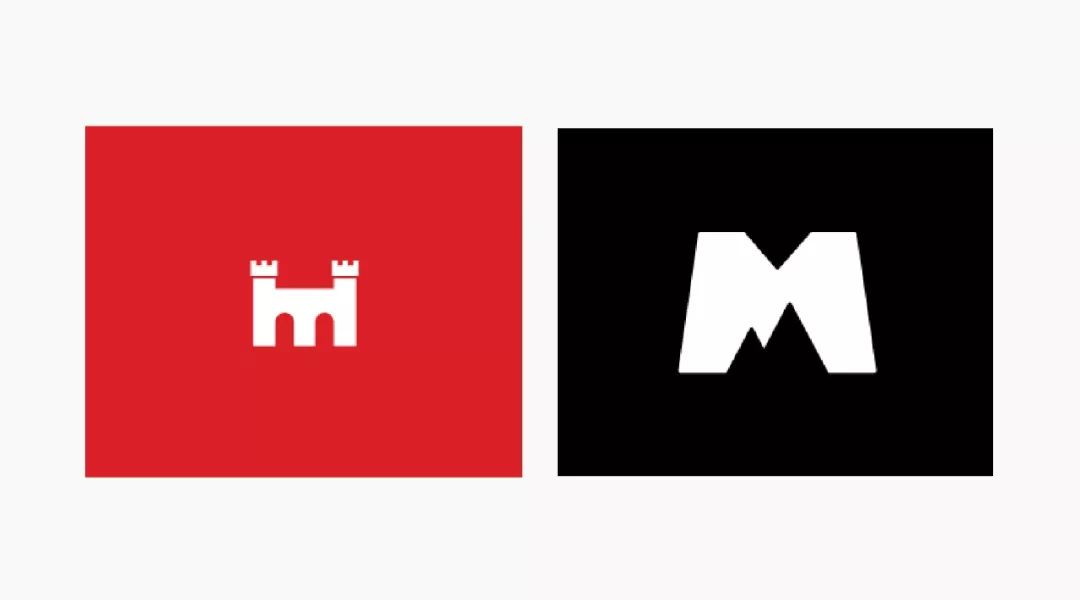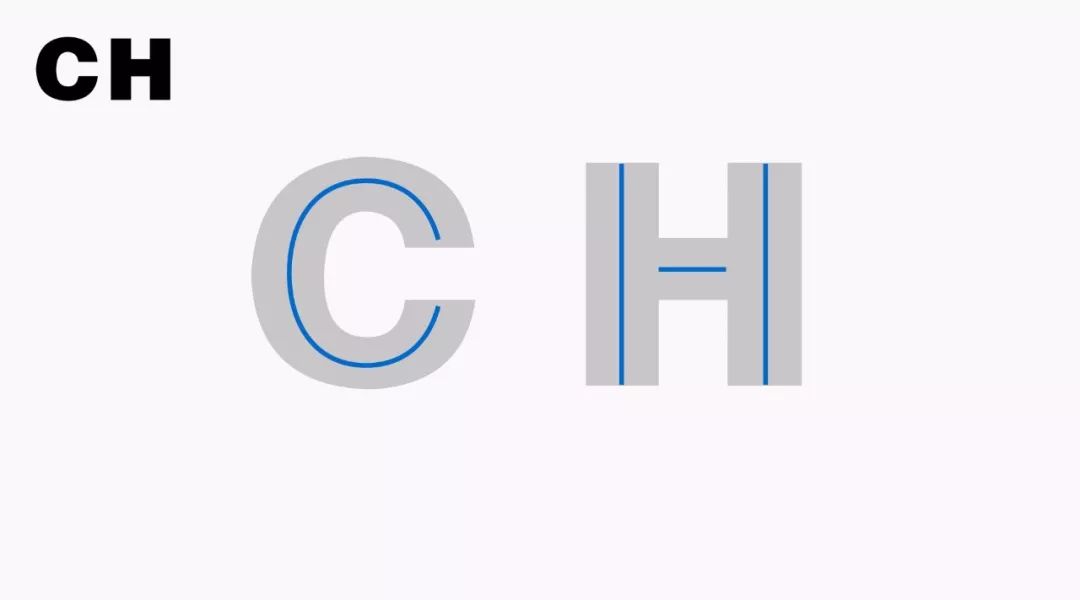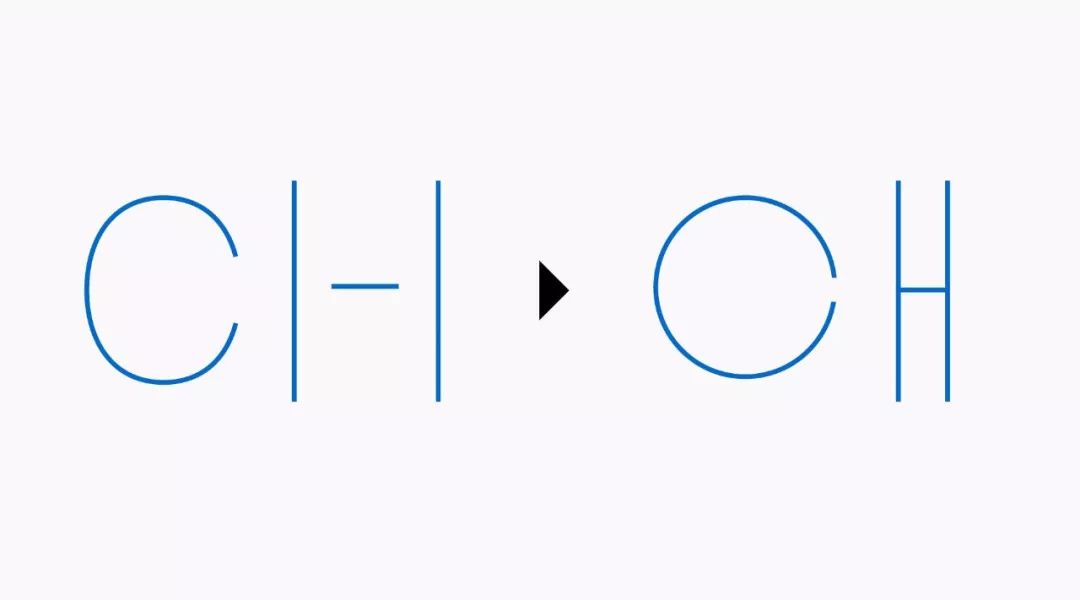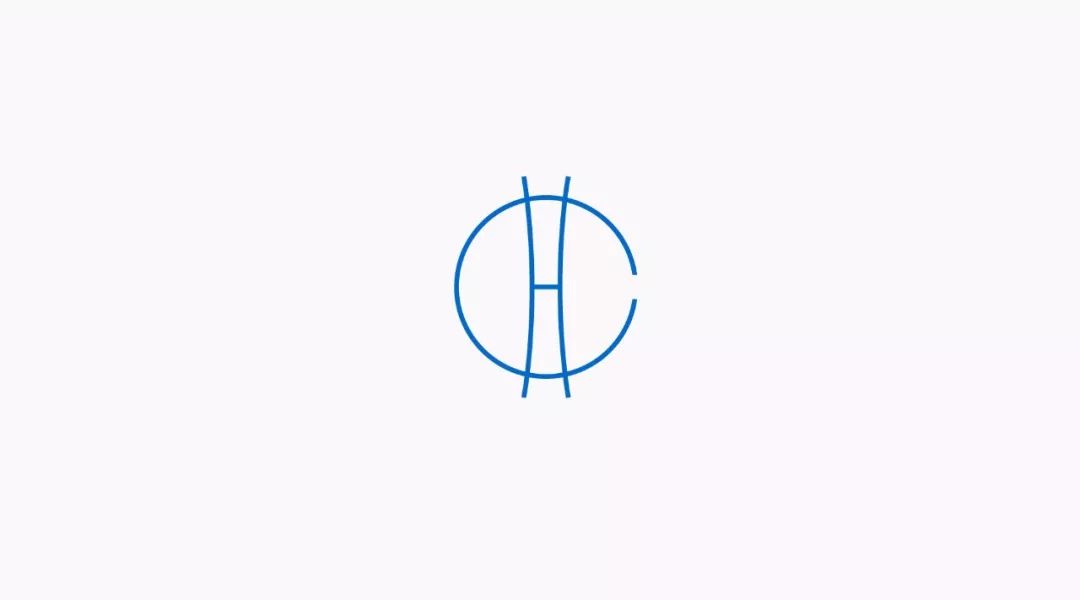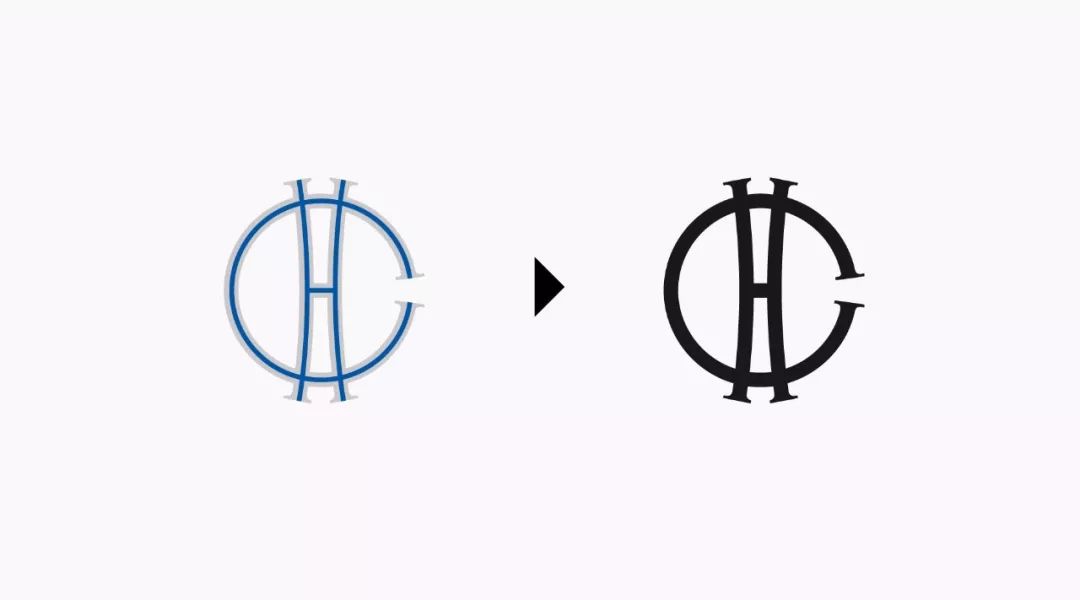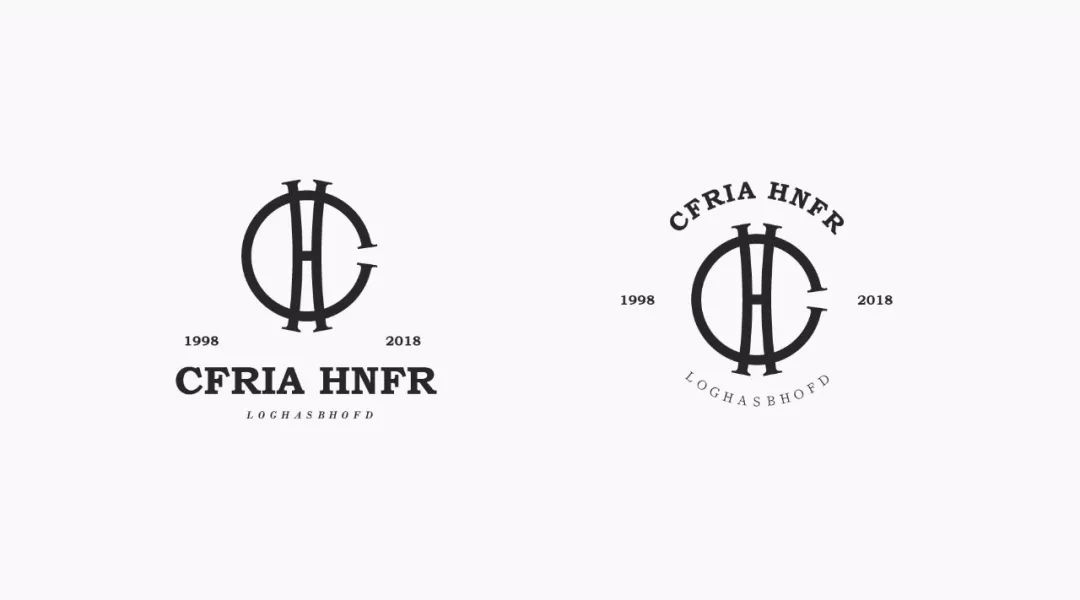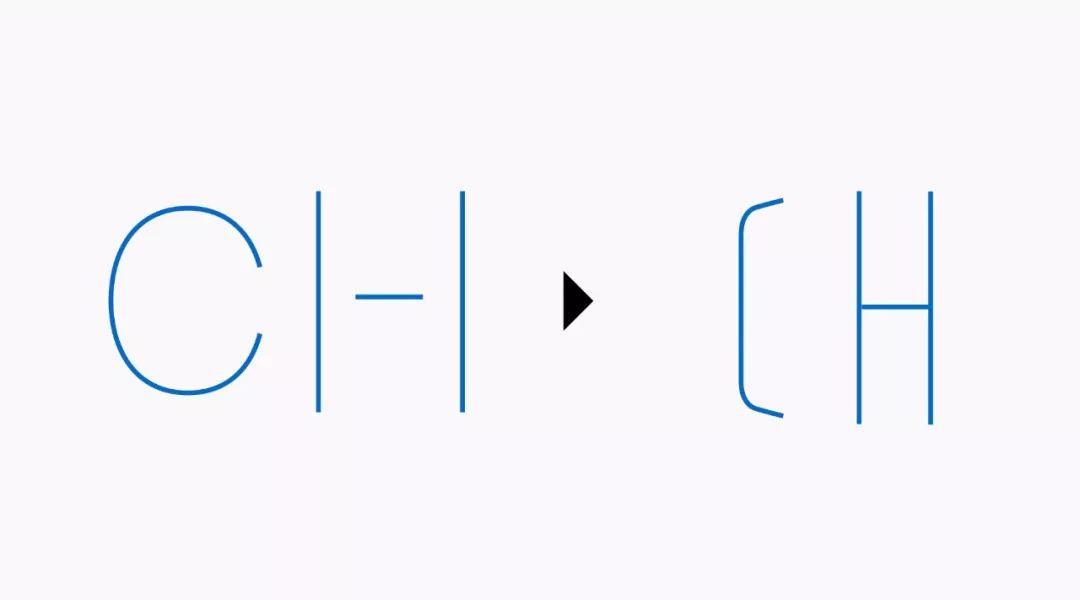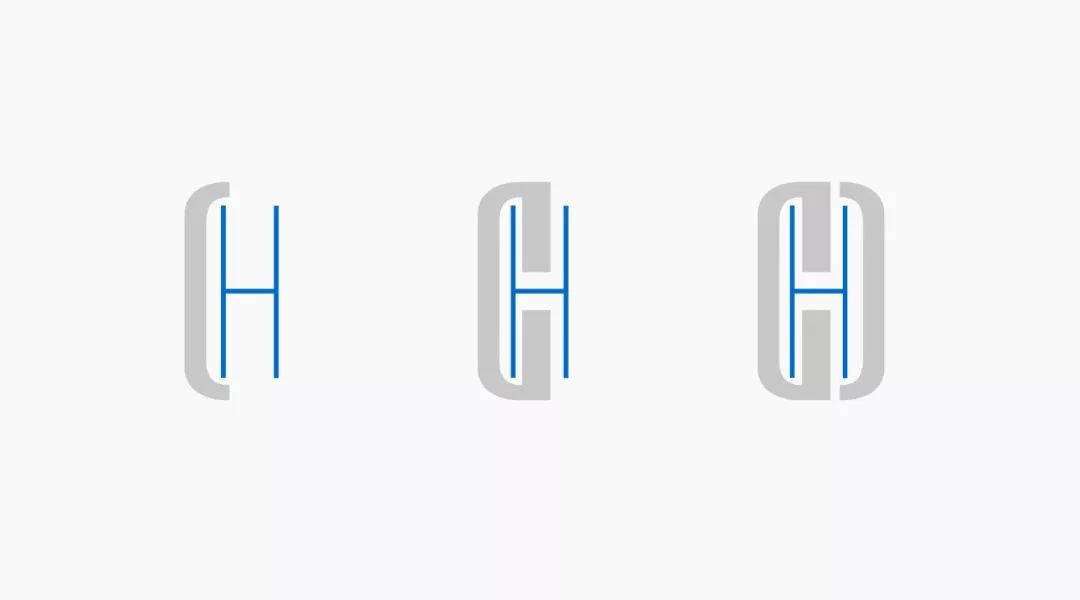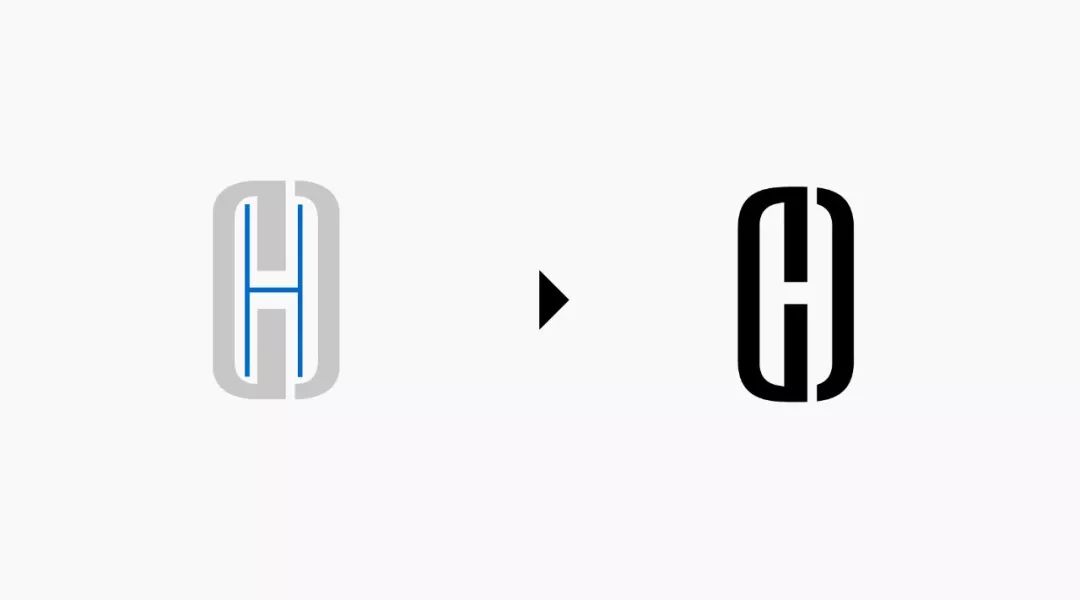
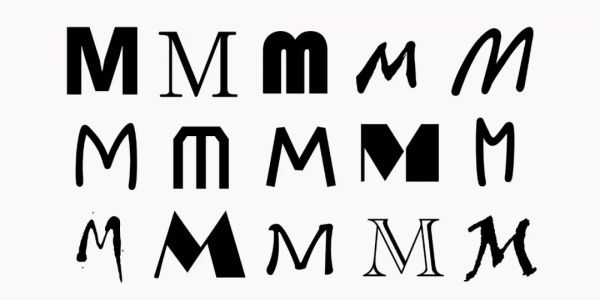
如何用首字母做一个漂亮的LOGO?
为什么很多公司用首字母做LOGO?
很多公司都用首字母或者首汉字做公司LOGO设计的元素,首字母的标志会把LOGO和品牌名称更紧密的联系起来了,减小了消费者看到LOGO后对其品牌的认知成本。
拿Mcdonald's和KFC为例子,如果你从未听说过这两个品牌LOGO,但是你得知一个品牌叫KFC,另一个是叫Mcdonald's,你会自然而然的把M的LOGO猜测成Mcdonald's,但KFC你就不能如此确定了。
所以首字母的LOGO更方便消费者最快速度建立标志和品牌之间的关系,达到认知和记忆效果。那我们如何去做一个优秀的首字母LOGO呢?
字母与具体元素结合
了解如何做一个首字母LOGO,就要先了解首字母LOGO有哪些种类,本文共提供3种首字母LOGO,其一是字母与具体元素结合,比如字母+动物,字母+建筑,等等。
这类LOGO,我们需要找到与字母特征相似的具体元素进行结合。M有很多种,那M的特征是什么?
通过上图以及我们平时对字母的理解,不难发现字母M的特点就是上面两个端点,下面三个端点。在保证特征不变的前提下,我们对路径进行一定范围的变化,并不会影响人们对字母M的辨识度,在字母M与其他字母结合时候,我们也更容易找到适合的元素。
比如M与鸟的结合,M与鹰的结合。
字母与抽象元素结合
当你必须使用的首字母找不到适合的具体元素时,我们可以放弃字母与物体结合的思路,用填充的方式制作LOGO,下面两个LOGO就是很好的例子。
最常见的填充方式就是点和线的填充,以点或线的构成方式制作LOGO,当M遇到波浪线会有这样的效果。在此思路上,我们可以保留M的特征对其造型继续调整,波浪线的间距,波频,LOGO的颜色都可以尝试变化。
双字母结合
大家都习惯用首字做LOGO,但是其实很多的标志都是在用两个字母做设计,可能是你没有发现,我来举一些例子:
这个LOGO叫darkbird 这是两个单词,分别是dark和bird,所以其实D和B 都适用于LOGO的创作,而BD又是轴对称图形,正好可以拼成一个猫头鹰的造型,猫头鹰可以很好的体现darkbird的含义。
这个LOGO的英文在颜色上我们就可以区分出他是两个词语构成的,首字母D和P可以作为LOGO的创作元素,将dp共用一个圆,中间的电波代表行业或者产品,形成现在这样的LOGO。
有些LOGO用到前两个字母,因为品牌名字也需要很简洁,BU其实也是两个词组的首字母,只是在标志上,我们看起来像前两个字母。
小米的LOGO并不是首字母X为元素,或者XM为设计元素做LOGO的,因为MI不仅有米字汉语拼音的概念,MI也有Mobile Internet的含义,体现了小米是做移动互联网的,所以除了首字母以外,还有很多双字母或其他可能性的LOGO设计。
我们总结上面这几个LOGO,如果是两个字母结合的话,要找到字母与字母之间的关联性。
如果现在有一个LOGO需要用字母C和H来结合,我们该如何把他们结合成一个LOGO呢?首先我们要分析字母的结构。字母C是椭圆形结构,字母H是矩形结构,如下图,蓝色代表字母的骨架。
接下来,我们的思路是把两个字母的特点放大后结合。于是我们把C变得更圆,H变得更细长,但是仍然保留字母CH的特点,我们一样很好的识别这两个字母。
下一步就是将两个字母结合,我们很自然的可以把H放到C圆形的中间,形成一个包围的关系,其中我微调了字母H竖的弧度,如下图。
但是到目前为止,蓝色线只是这两个字母的骨架,并不是最终的LOGO,我们可以在上图骨架的基础上对两个字母进行不同形式的装饰,如下图。
最后再进行细节调整,添加文字排版就可以形成一个很不错的双字母结合的LOGO了。
还有别的办法把两个字母结合成LOGO,回到骨架这张图,刚才我们是把两个结构极端化,这次我们要把两个字母统一化。
我们把椭圆形结构的C尽可能的变得竖直,让他可以与H发生统一的关系。在下图你会发现C的骨架与H的右半部分已经是一样的了,我们可以直接用C来替换H的右侧结构,然后C换一个颜色就可以了。
但是亮哥觉得这样做,最后LOGO会显得有些简单,所以我们可以尝试其他的方式,因为C和H的竖我们已经找到了共同点,我们不用C成为H的一部分,而是用C围住H的一部分。思路大概是下面这样,用C的造型围住H的骨架。
接下来把H的骨架隐藏,调整负空间H以及正空间C的比例关系,确保造型舒适。
加上文字和排版,这样就用两个字母统一的方式又诞生了一个新的标志,C和H的元素都包含在图形内
-总结-
本文提供了3种首字母设计的类型,分别为字母与具象元素结合,字母与抽象元素结合,字母与字母结合。并且简述了为什么可以用首字母做LOGO设计的元素。